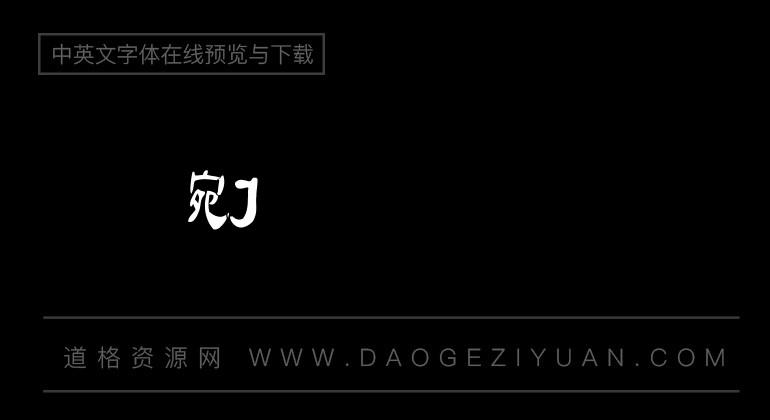
金梅毛隶破裂字繁
金梅毛隶破裂字繁是一种汉字字体,它的特点是字形繁复,笔画粗细不一,且每个字都有破裂的感觉,极具艺术性。它的字体设计师是来自中国的设计师毛隶,他把金梅花的精美结构融入到字体中,使字体更加精致,更具艺术性。金梅毛隶破裂字繁字体适用于各种广告宣传、海报、展板、书籍封面、礼品包装等,能够给人以古典、精致的视觉感受。
金梅毛隶破裂字繁是一款非常不错的手写艺术字体,具有很好的视觉感,适合于文化类的宣传设计、商业类品牌的广告和产品包装设计以及个性化文字排版等较多场景。